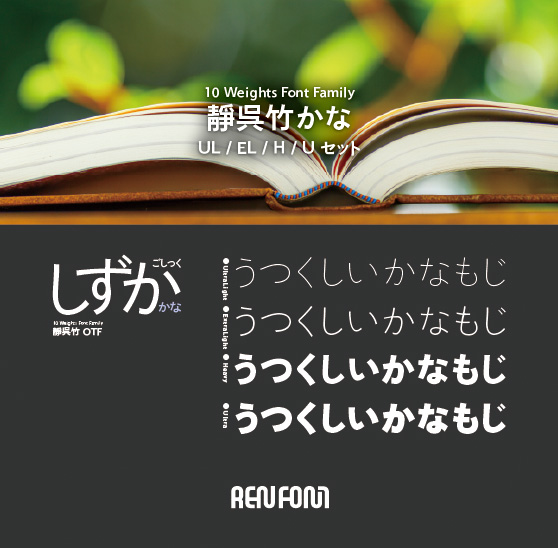
靜呉竹かな-タイトル・大見出し用4ウェイトセット(UL/EL/H/U)
靜呉竹ファミリーは、 読むことに専念してもらうために開発した書体。本文組みに使ってみてください。ほんわかとした、あたたかく読みやすい文章になるはずです。縦組み、横組みともプロポーショナル加工を加えています。また、横組みに限り(欧文も)、ペアカーニングもほどこしました。本ULウェイトは、ヒラギノ角ゴシックW0、AXIS Std ULなどにベストマッチ。タイトル・大見出し用3ウェイトセット。